霸道鹤棣体,该手写体单人旁的撇笔画整个下压,稳重而不显压抑。横笔画的加长与撇笔画的缩短,使得字体有一种扁平风。三点水的写法使字更加的扁平。横笔画的波浪写法让字体变得更加有意思,非常适合在一些卡通动画上添加字幕使用。
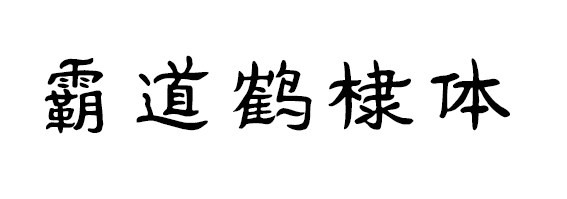
锦鲤本鲤飘逸洒脱的笔划彰显不羁的性格,外松内紧的结构昭显心胸的豁达,拼音的辅助更为孩子打开方便之门,自主学习无压力。
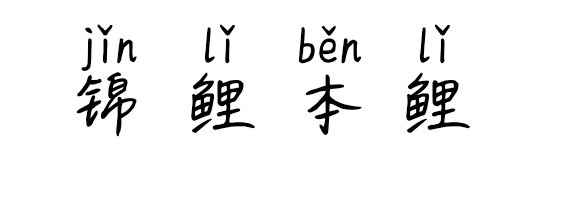
胸中点点墨,写出大智慧。点点墨体,一点点墨水滴在纸上写出的字体;既遒劲有力又不失文雅风韵的特色字体。